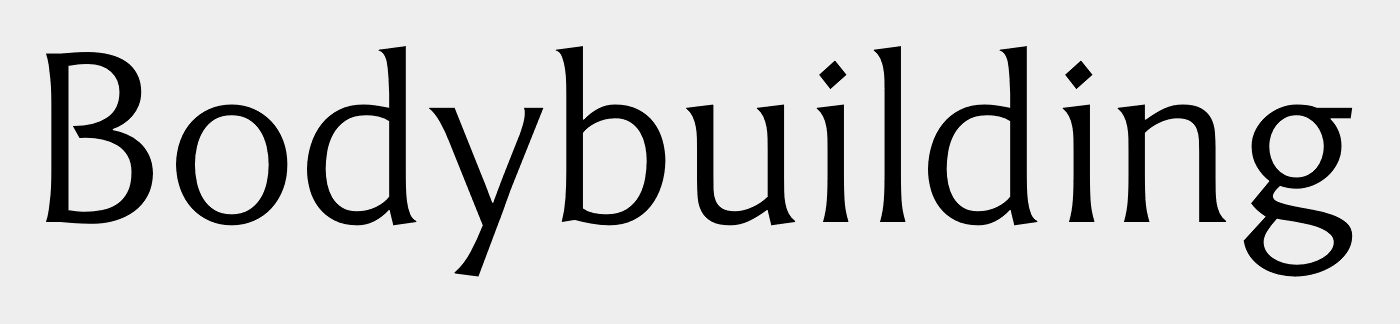
Typo für Personaltrainer gesucht
ich arbeite gerade an einem Homepage-Redesign für einen Personaltrainer. Es richtet sich also an Fitness-affine Menschen.
Werte die mit dem Auftritt vermittelt werden sollen
Kompetenz - gerade wenn es um den eigenen Körper und die Gesundheit geht möchte man in guten, kompetenten Händen sein
Sympathie - der Trainer ist eine extrem sympatische Person, was definitiv ein Aushängeschild ist
Stärke - Kraftsport, Bodybuilding, Fitness, etc da werden Gewichte bewegt, dieses Gefühl als hätte man gerade einen Baum entwurzelt, sollte sich auch irgendwie in der Schrift wiederfinden
Disziplin - ob nun in Bezug zu der Regelmäßigkeit der Fitnessclub-Besuche oder auch der gesunden Ernährung
Überzeugungskraft - letztlich bleibt es Werbung um mehr Kunden zu gewinnen, das Schriftbild sollte auch zu den verkäuferischen, überzeugenden Texten passen
Ich suche in der Art also etwas starkes, klares mit geraden Konturen. Eine Typo die auch gern etwas schwerer wirken kann, in Anlehnung an die schwere Hantel.
Vielleicht haben einige von euch ein paar Idee, würde mich sehr freuen, da ich mich echt etwas schwer tue.
Was du suchst ist bestimmt keine Typo, sondern eine Schriftart – Schriftart ≠ Typo ;-)
Und mal ganz ehrlich ...
dieses Gefühl als hätte man gerade einen Baum entwurzelt, sollte sich auch irgendwie in der Schrift wiederfinden
... wie soll das denn gehen? :-?
Solche Gefühle kannst du durch die gesamte Gestaltung, Bilderwelten und Texte etc. vielleicht ansatzweise erzeugen, aber mit der Schrift alleine wird das nichts :-o:mad:
Was mir zu dem Rest einfällt: Ich würde wahrscheinlich irgendwas geometrisches wählen. Da es wahrscheinlich auch günstig oder gratis sein soll, guck doch mal hier nach. Die meisten Schriften dort kannst du auch frei für Websites* benutzen. Die Montserrat kann z. B. auch richtig fett.
Ich hab mal für ein ähnliches Szenario (Schwerpunkt war aber gesundheitsorientierte Fitness, nicht Bodybuilding) die Optima verwandt, da der Aspekt Vertrauen eine große Rolle spielt und die Optima zumindest unterbewusst die Seriösität einer Serifen-Schrift  bei der Modernität einer Sans mitbringt.
Habt ihr schon eine Zielgruppenanalyse gemacht? Junge Körperfetischisten kann man bestimmt auch mit einer Bootcamp-Stencil ansprechen, älteres, mehr auf körpererhaltendes bedachtes Publikum wird sich wohl eher von einer seriösen Schrift angesprochen fühlen.
Hab mich grad so ein bischen in die Epigraph verguckt (geiler Name übrigens):
Na, welche Schriftarten hast Du denn schon ausprobiert und dann wieder verworfen?
Ich persönlich hätte hier mal eine Liste dessen gepostet, mit dem ich mich schon auseinandergesetzt und aus irgendeinem Grund wieder verworfen habe.
So wie Du die Frage stellst kommt es mir so vor, als ob wir Dir nur die lästige Recherchearbeit abnehmen sollen.
Leider gibt es die große gelbe Fontbibel ja nicht mehr zu kaufen, eine gute Tasse Kaffe, entspannte Musik und 2 Stunden Zeit und man hatte so viele Ideen … allein beim Gedanken daran hab ich schon eine Idee: die Beton (extrafett als Auszeichnungsschrift).
Beton
Ich finde, die hat ein erzhäßliches y. Würde ich auch nicht ansprechend finden, aber das kommt, wie gesagt, auf die Zielgruppe an.
Bootcamp-Stencil
die Beton (extrafett als Auszeichnungsschrift).
Da hätte man sogar die Stencil mit dabei :-P
Vielleicht einen der fetten Schnitte der Milo Slab  für Schaugrößen und die Milo Sans für den Fließtext. Die scheint auch ganz ordentlich gehinted zu sein – ist jedenfalls unter Windows auf dem Bildschirm gut lesbar. Und wenn du dich auf drei bis vier Schnitte beschränkst, kostet das auch nicht die Welt. Die fette Milo Slab steht fest auf ihren Füßen, ist aber nicht schwerfällig.
Im Übrigen ist der Unterschied zwischen Kraftsport und Fitness-Training schon ziemlich groß. Optima-ähnliche Schriften kann ich gut mit Fitness zusammenbringen, aber mit Kraftsport? – beim besten Willen nicht. Aber ich gestehe, dass ich die Optima und alle ihr ähnlichen Schriften auch einfach nicht mag. Die Serifen-Rudimente erinnern mich ein wenig an die eingeschnürten Füße eines chinesischen Mädchens.